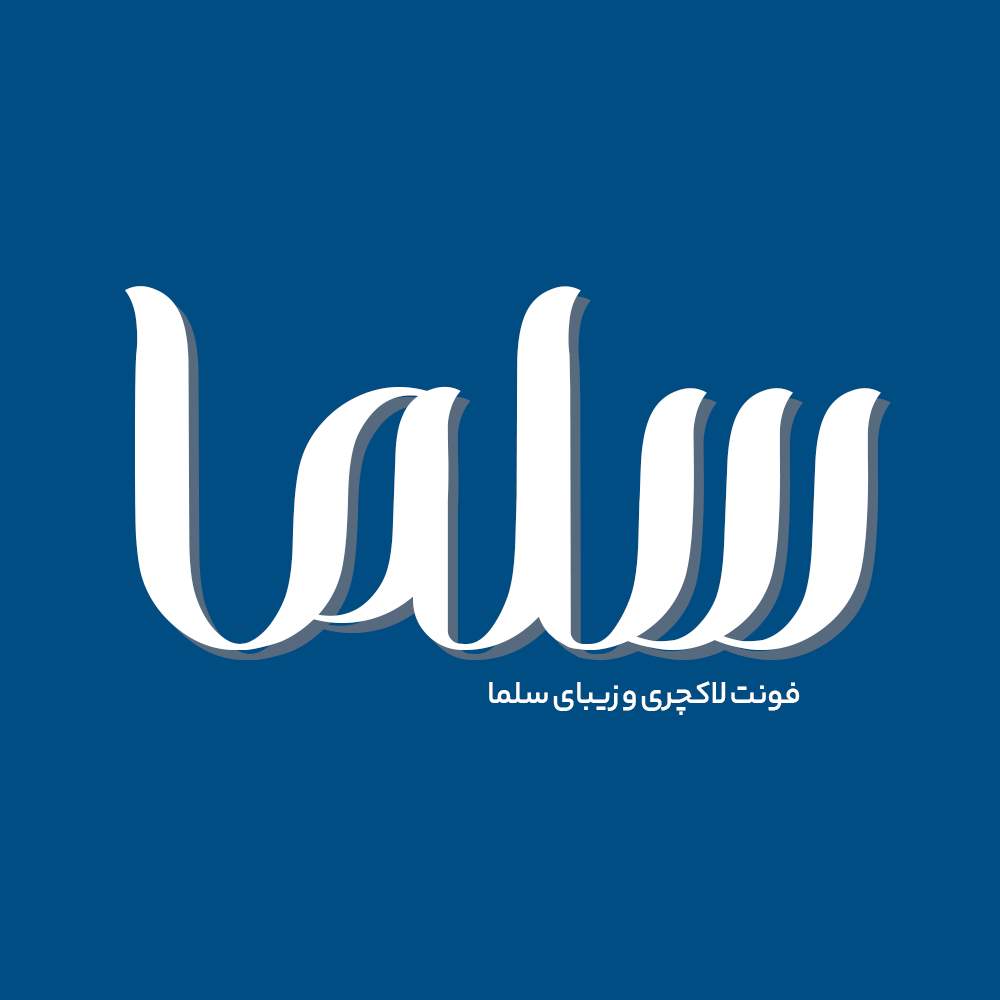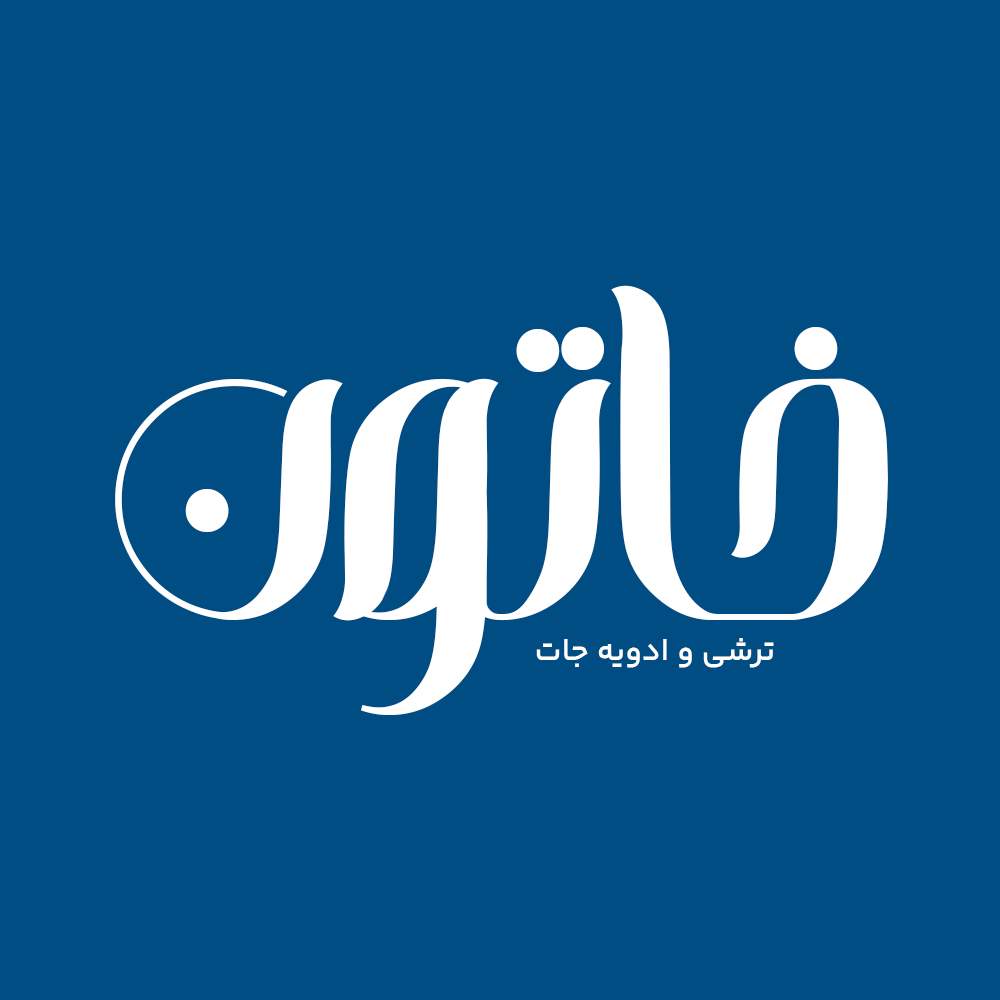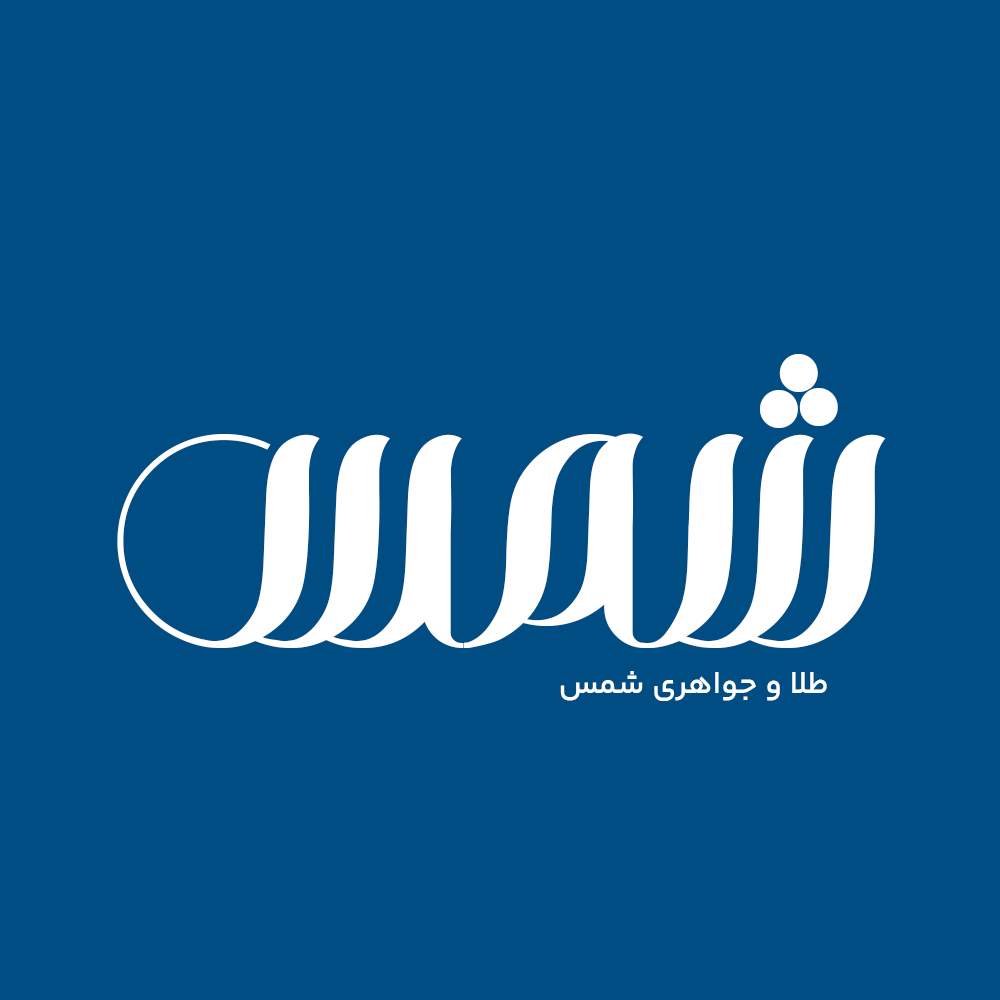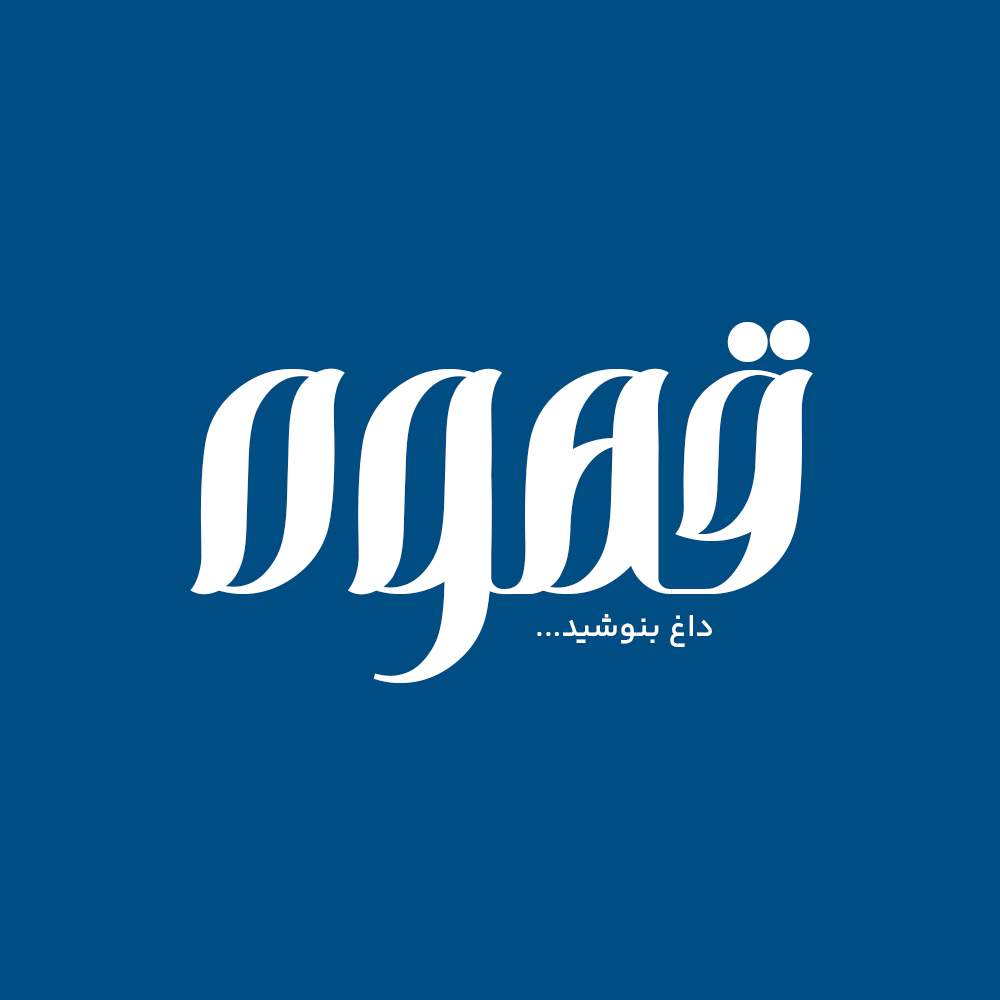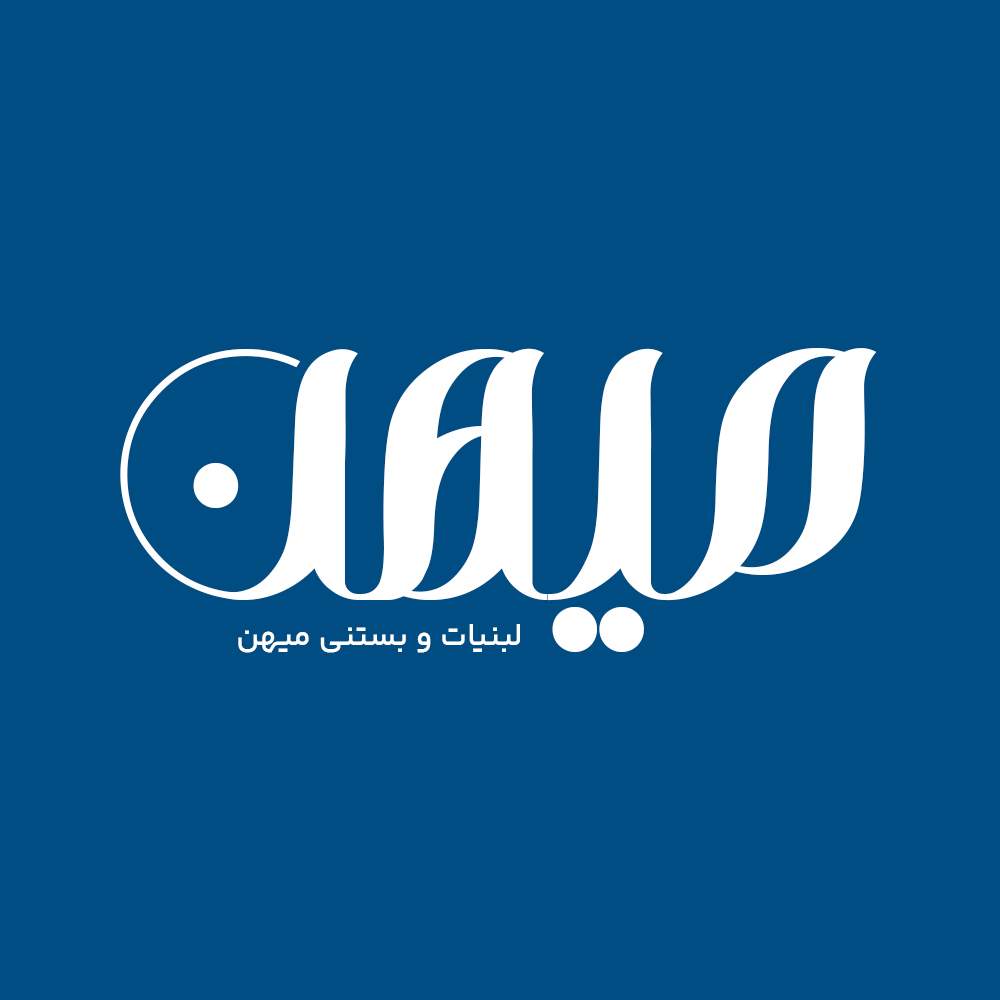
فونت فارسی سلما Salma Font
فونت فارسی سلما یک فونت خاص با ساختاری زیبا و متفاوت می باشد که به شما این امکان را میدهد با تایپ ساده کلمات تایپوگرافی هایی…
فونت فارسی سلما یک فونت خاص با ساختاری زیبا و متفاوت می باشد که به شما این امکان را میدهد با تایپ ساده کلمات تایپوگرافی هایی در سبکی خاص و زیبا خلق کنید. این فونت با ساختار حروف خود مناسب استفاده در لوگوهای نوشتاری می باشد. همچنین از این فونت در طراحی تابلوهای چلنیوم هم به دلیل ساختار منحصر به فردش می توانید استفاده کنید. در ادامه برای شما نمونه تایپ های این محصول حرفه ای رو آماده کردیم که میتونید مشاهده کنید.
پیشنمایش و نمونه تایپ های فونت سلما
فونت فارسی سلما Salma Font